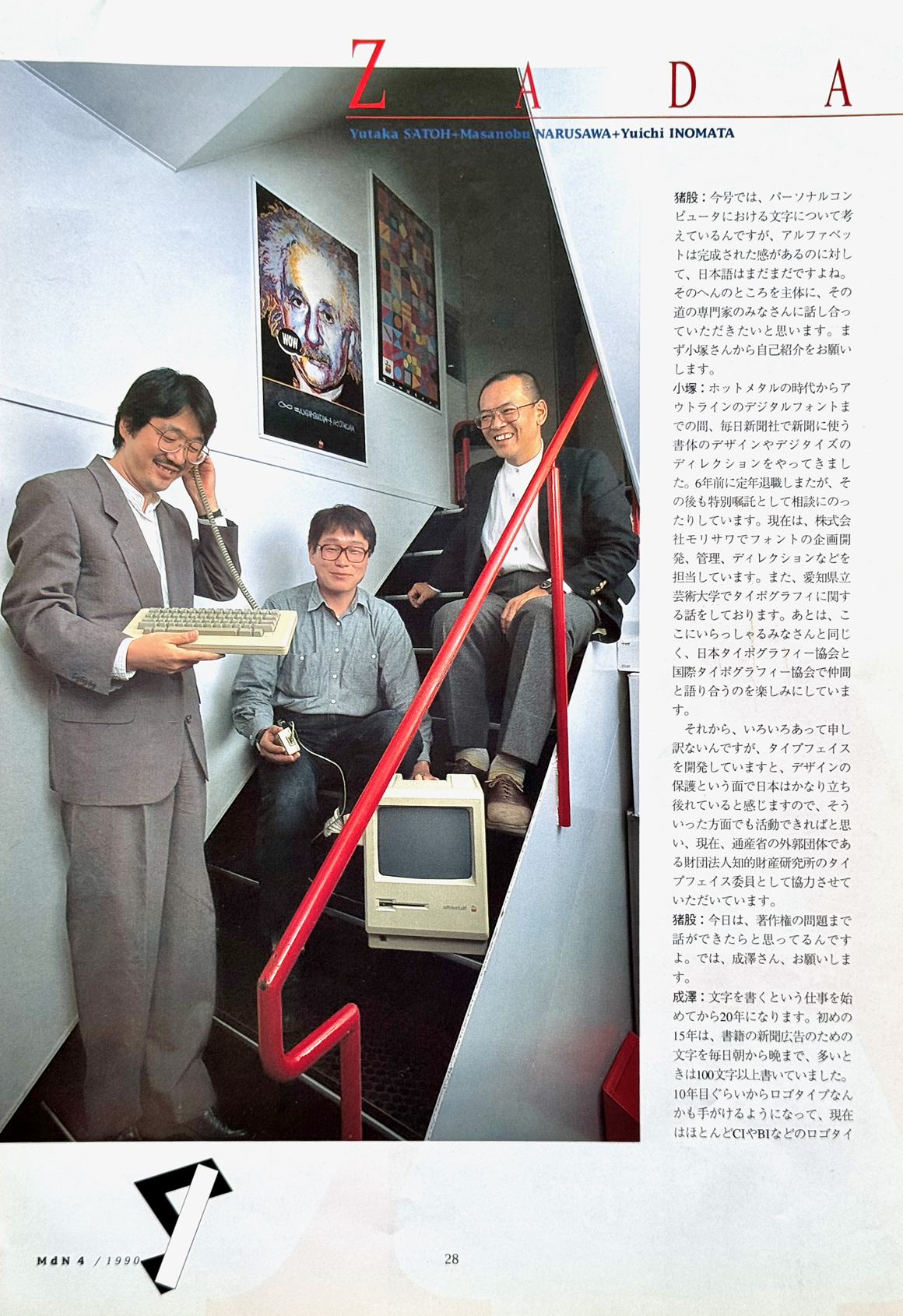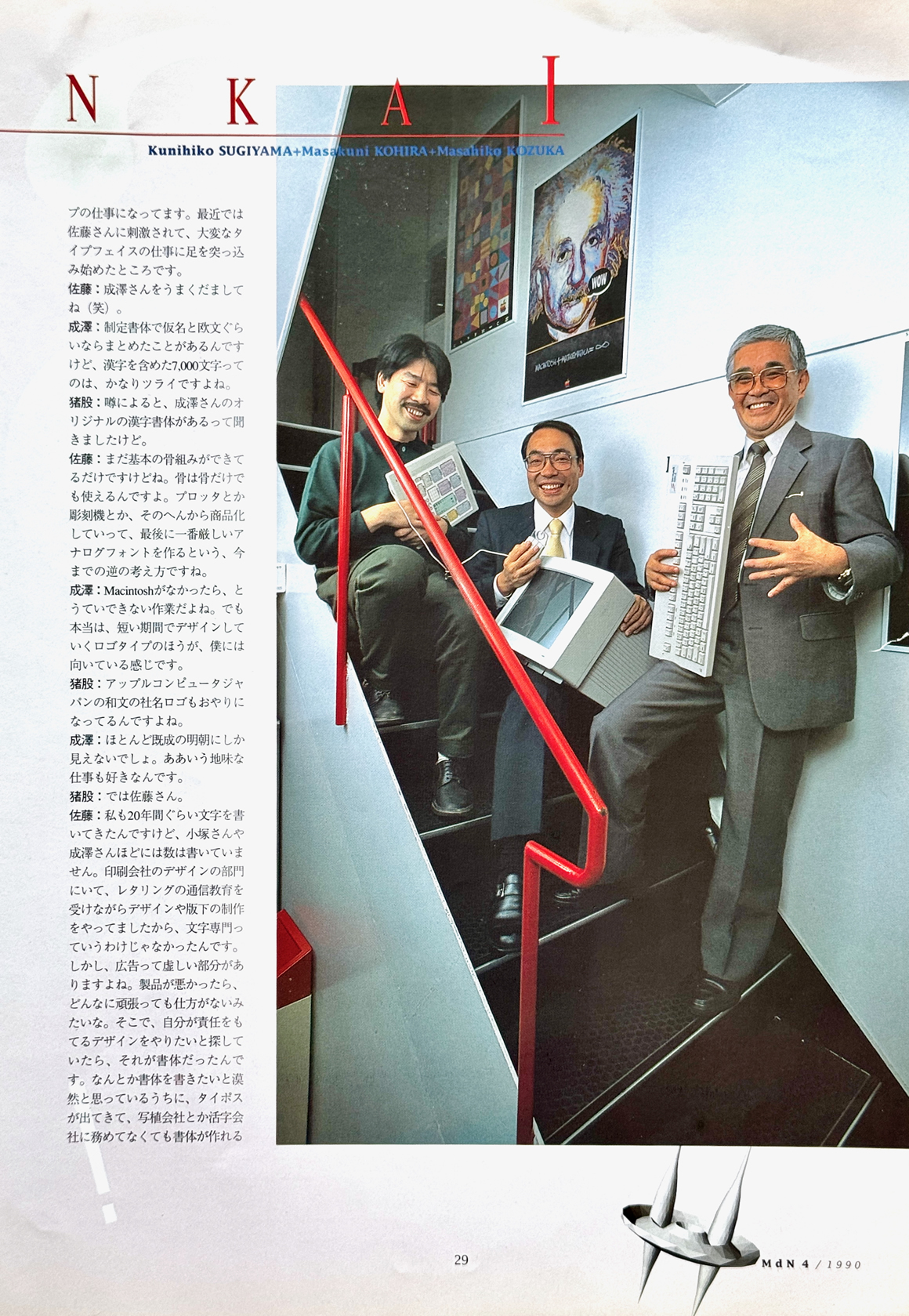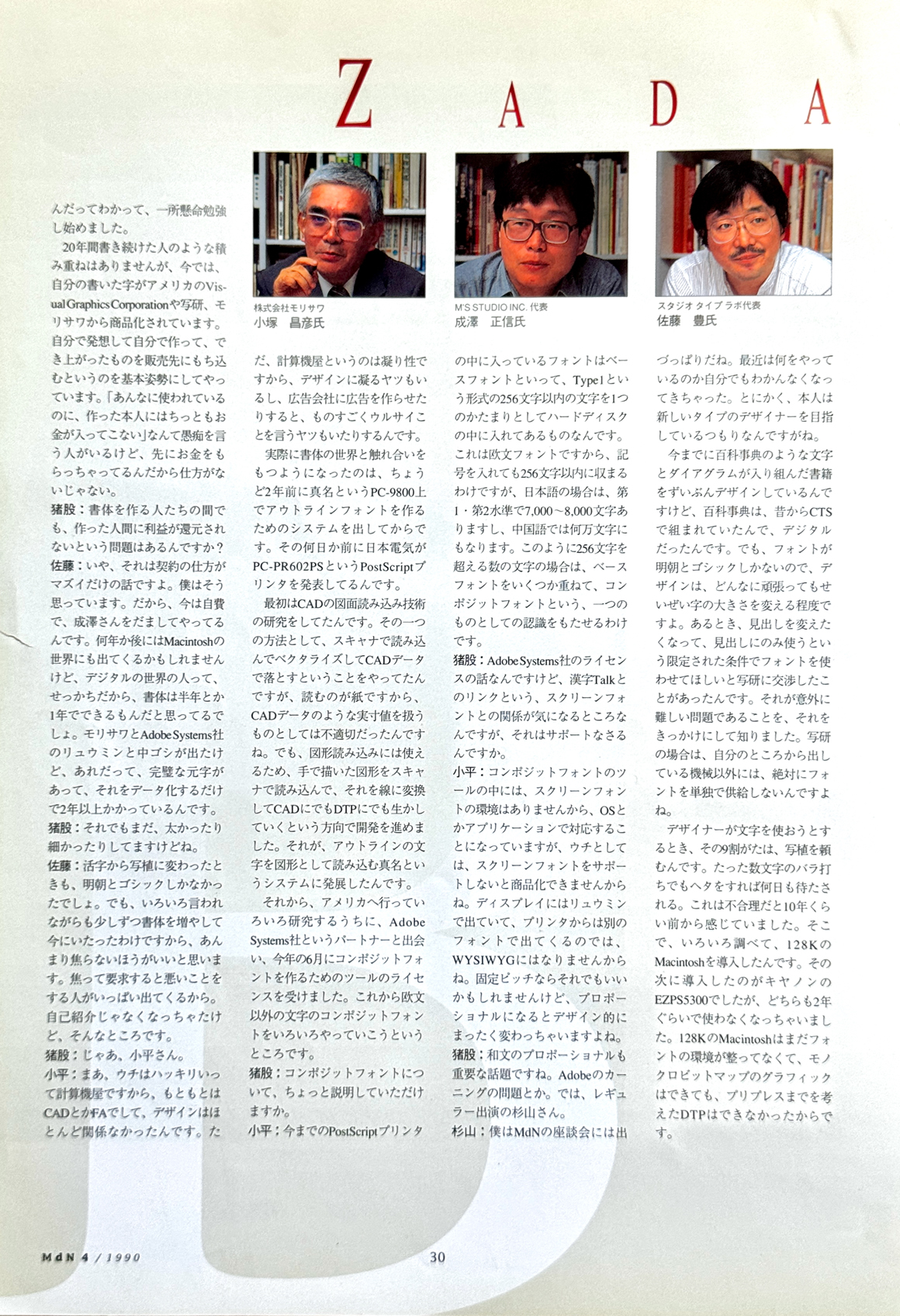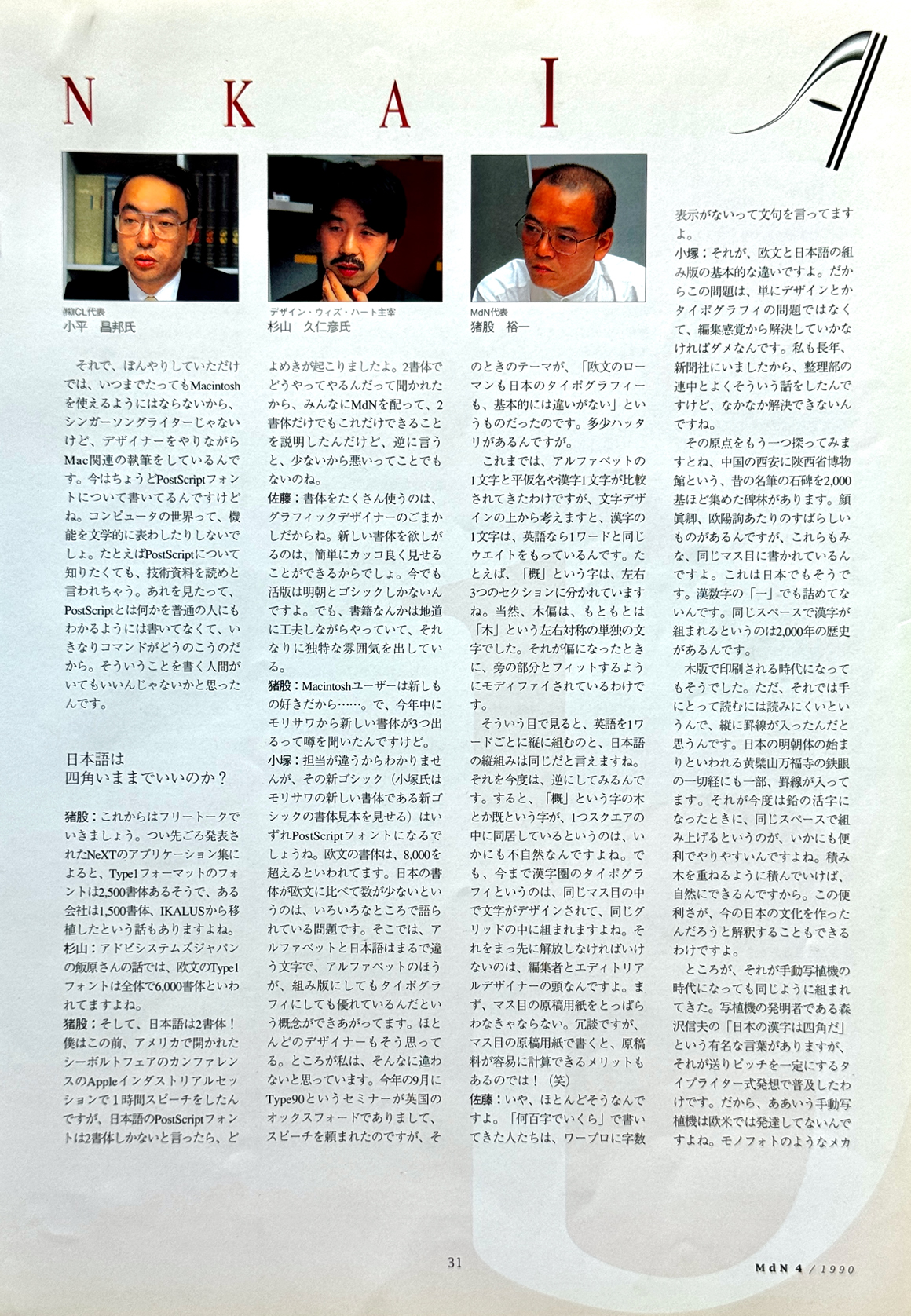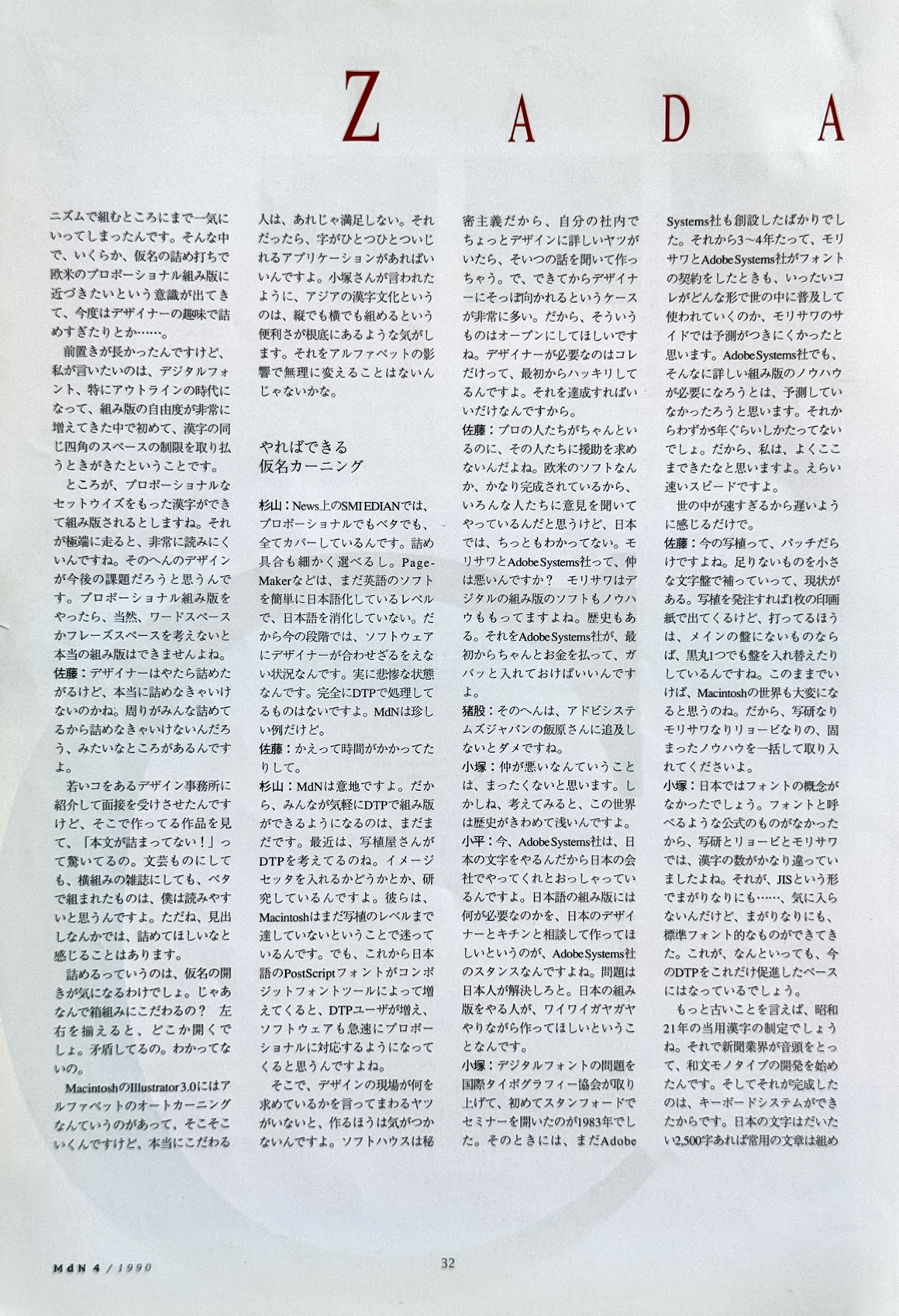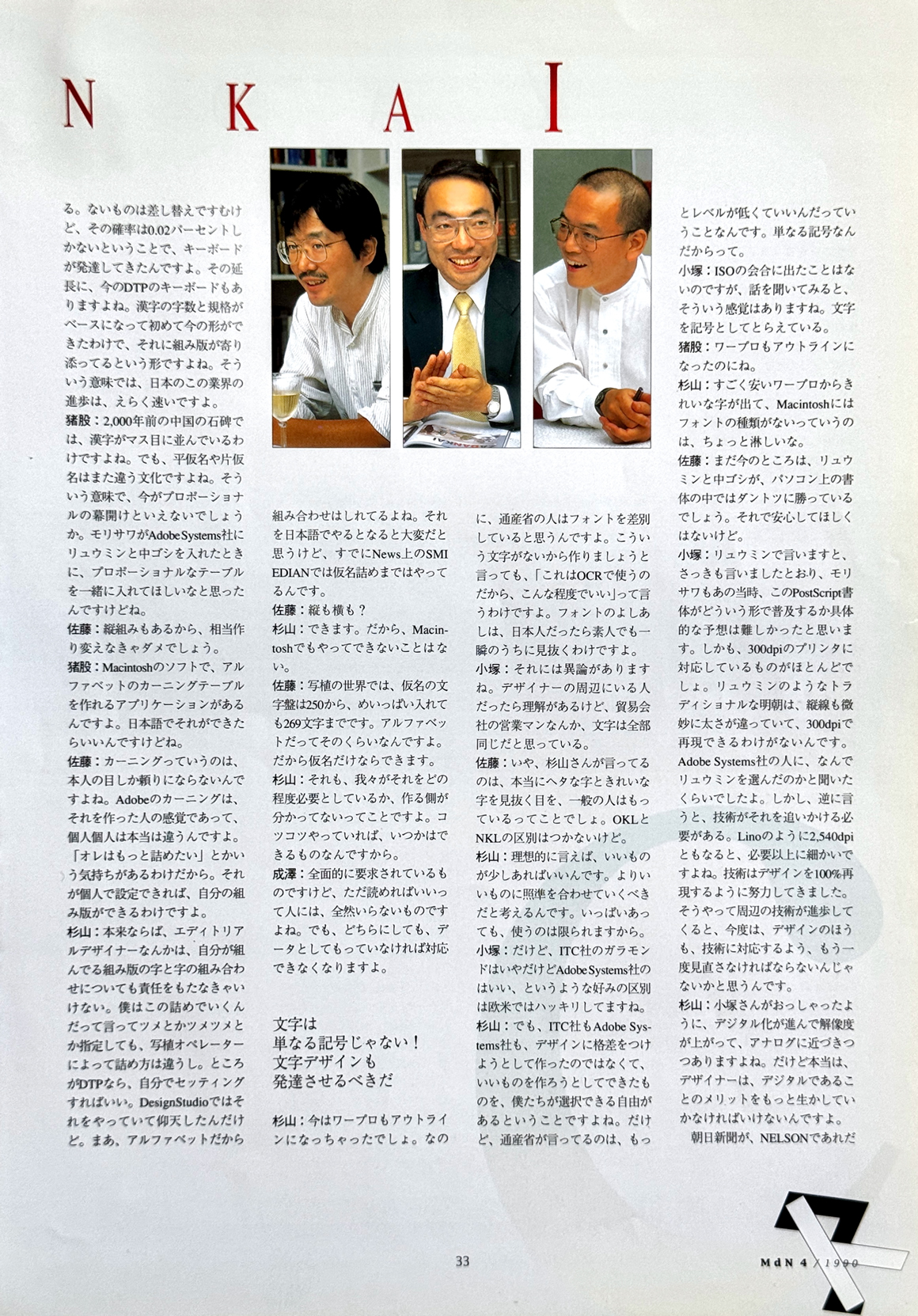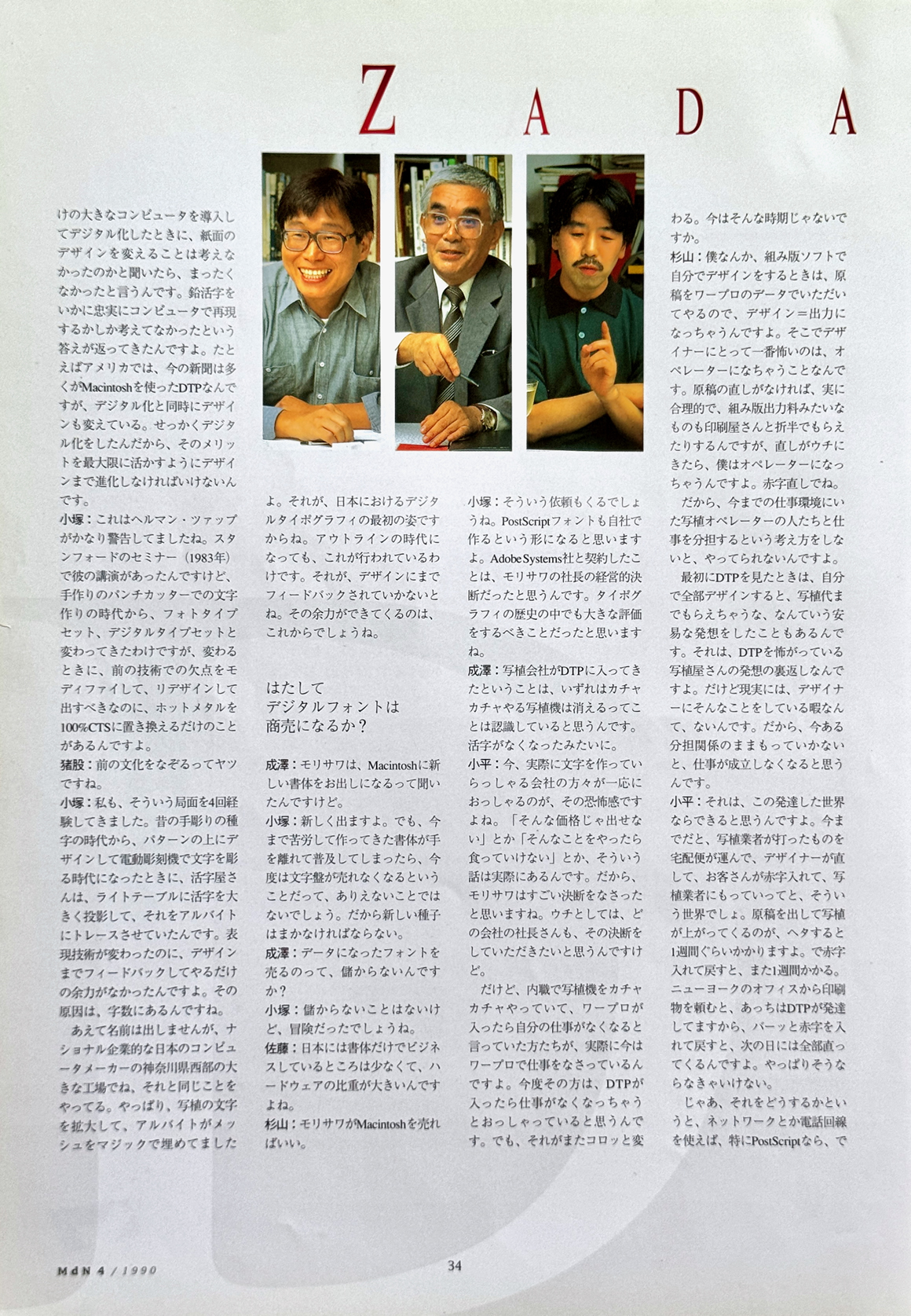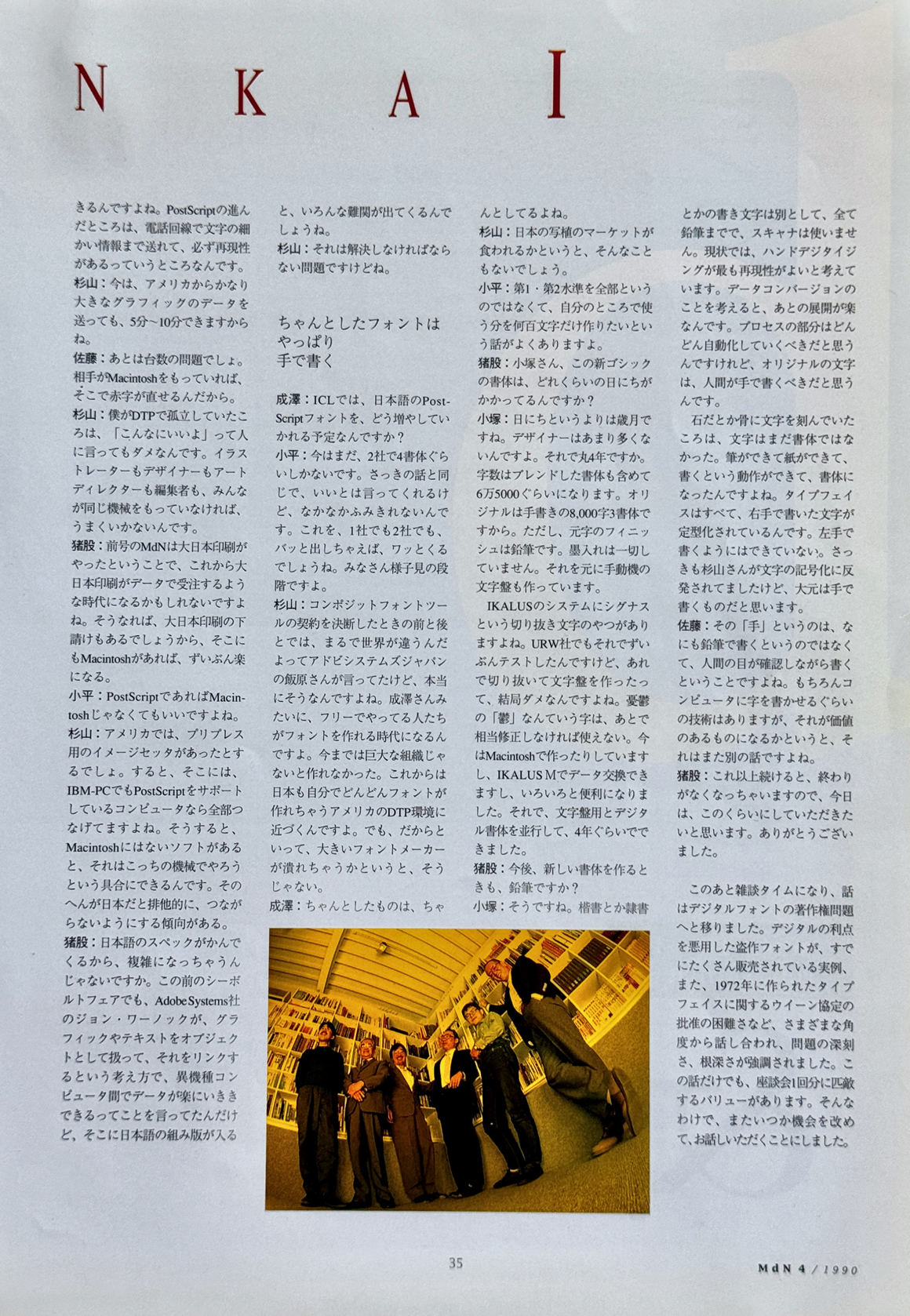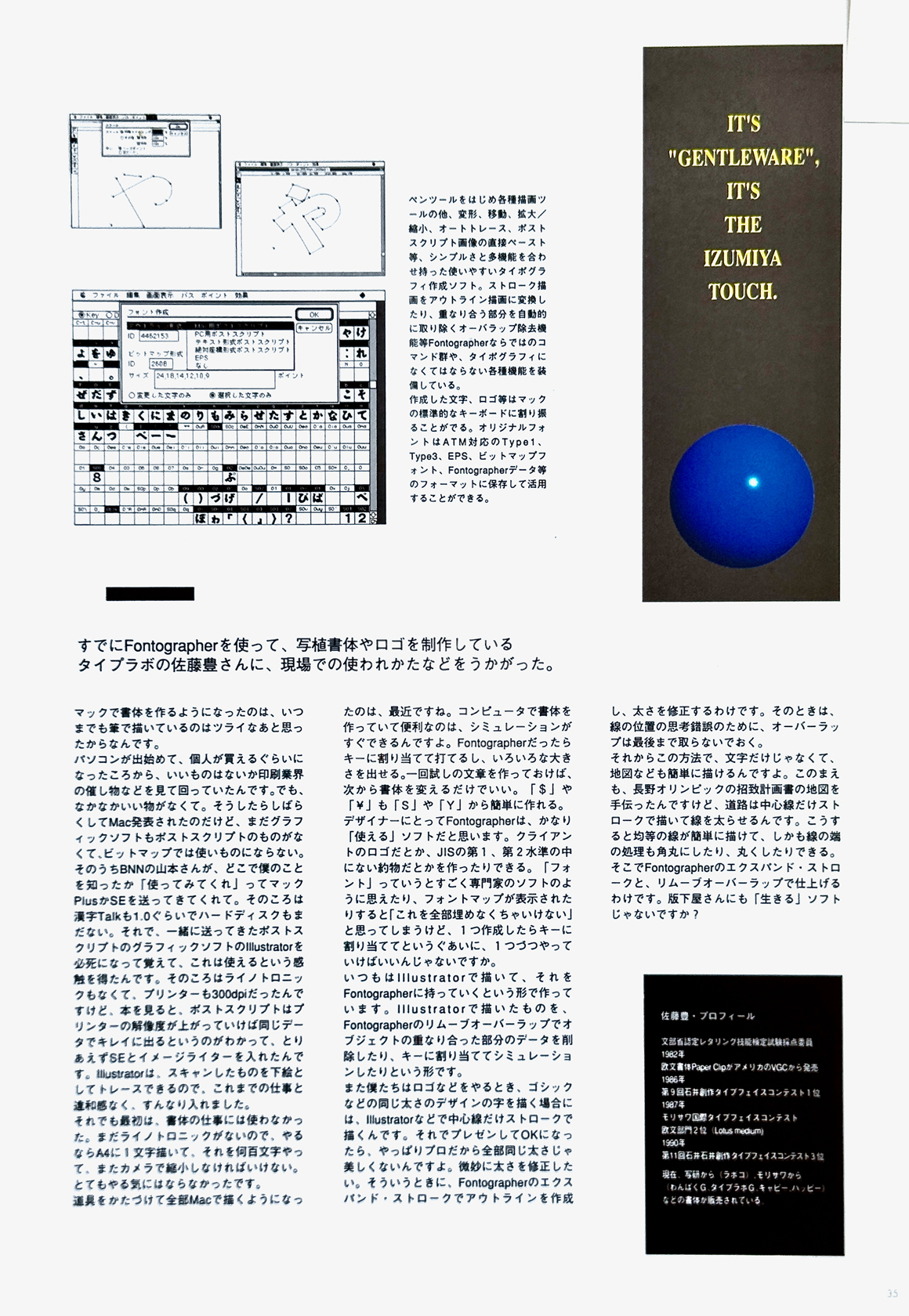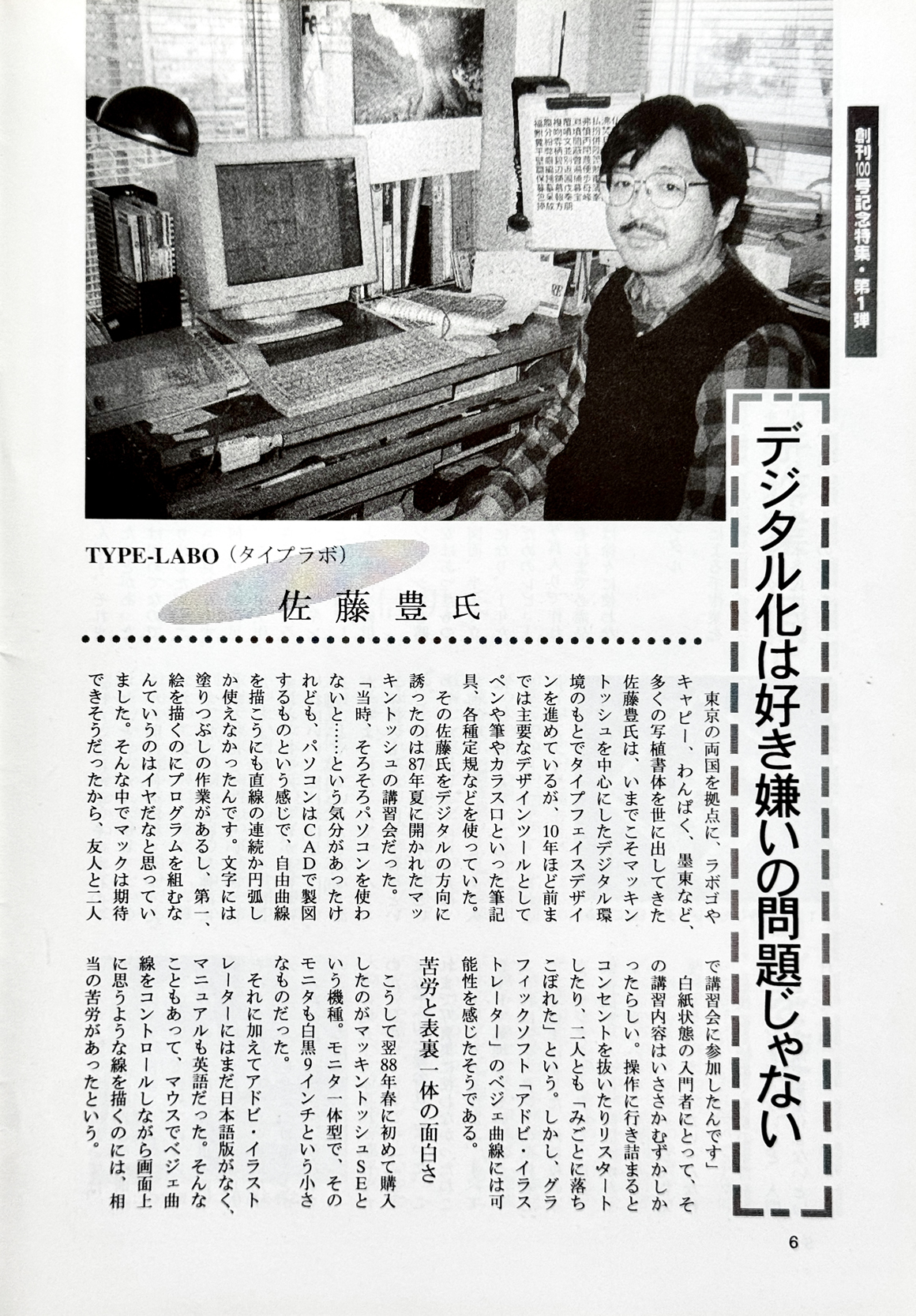
過去に話したことや書かれた記事を…そのままリアルな画像で紹介するページ(1987〜1997)
書体デザイン会に新たな風を(1987) MONZ10月号
国際タイプフェイスコンテスト・モリサワ賞の欧文部門で2位受賞の記事。
MONZの前身は「写植タイムス」という業界紙。
オリジナルフォントを作る(1988) BugNews8月号
BNNという出版社から1985年に創刊されたパソコンカルチャー雑誌「BugNews」。
実践イラストレーター講座という連載シリーズのフォント篇。
アルファベットが個性豊かに(1990) B・TOOL 9月号
Paper Clip書体がアメリカの会社から発売されたり、Lotus Mediumが世界的なコンテストで入賞したことで、取材された。
B-TOOL(ビー・ツールマガジン)は、ナツメ社から発行されていた文房具専門雑誌。
ZADANKAI(1990) MdN4月号
デザイン・グラフィックの総合雑誌として人気のあった「月刊MdN(エムディエヌ)」。
撮影用に家を1軒借りて収録、とても豪華な座談会だった。
参加者:小塚昌彦・成澤正信・佐藤豊・小平昌邦・杉山久仁彦・猪俣裕一
現場での使われ方をうかがった(1991) MacLab3月号
MacLabは、いづみや(現:株式会社Too)が発行していたPR誌。
当時いづみやでは、Fontographerというフォント作成アプリを販売していたので、その販促記事。
{特集]タイポグラフィ(1992) 日経デザイン3月号
日経デザインは、日経BPが発行しているビジネス向けデザイン誌。
タイポグラフィ特集ということで2ページ使って紹介してくれた。
デジタル化は好き嫌いの問題じゃない(1997)APIA 4月号
全日本DTP工業会(現:GCJ)が発行していた機関紙の100号記念記事「〈デジタル化〉への道」。
フォント制作者の“ふぉんとの”苦労とは(1997) ホットDTP 6月号
下の記事と同じ媒体の同じ号だが、巻末ページにあるDTP万華鏡というコラム記事…。
タイプフェイス作りの達人(1997) ホットDTP 6月号
画像2枚目の「フォントはこうやって作ります!」は、取材中に突然言われて作ったので、あまり見せたくない低レベル…。
あの人の仕事場(1997) プロフェッショナルDTP 12月号
この頃の事務所は、両国プラザからタカシマ両国の13階に移転している。
国際タイポフェイスコンテスト金賞(1997) デザインの現場
8月号
美術出版社から発行されていた「デザインの現場」の、DESIGN MIX JUICEという人気ページ。